สำหรับใครที่กำลังหาฟอนต์ไทยไว้ใช้งาน ไม่ว่าจะเป็นงานส่วนตัวหรืองานเชิงพาณิชย์ ทีมงานได้คัดเลือกฟอนต์ไทยสวย ๆ หน้าตาเป็นมิตร มาแนะนำให้ดาวน์โหลดกันค่ะ
แนะนำ 10 ฟอนต์ไทย สวยเป็นมิตร ใช้งานฟรี คัดสรรจาก Google Font
1. Kanit
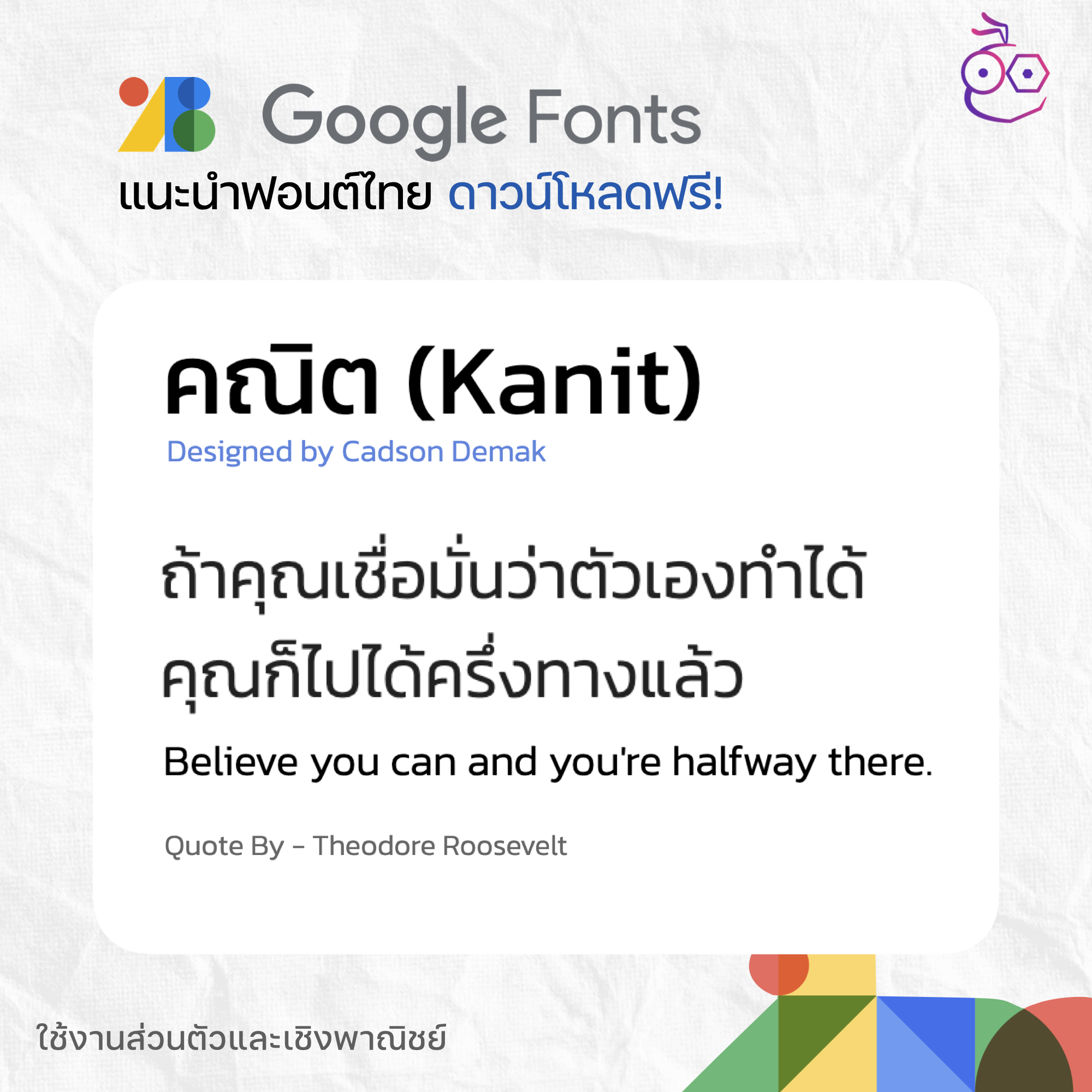
2. IBM Plex Sans Thai
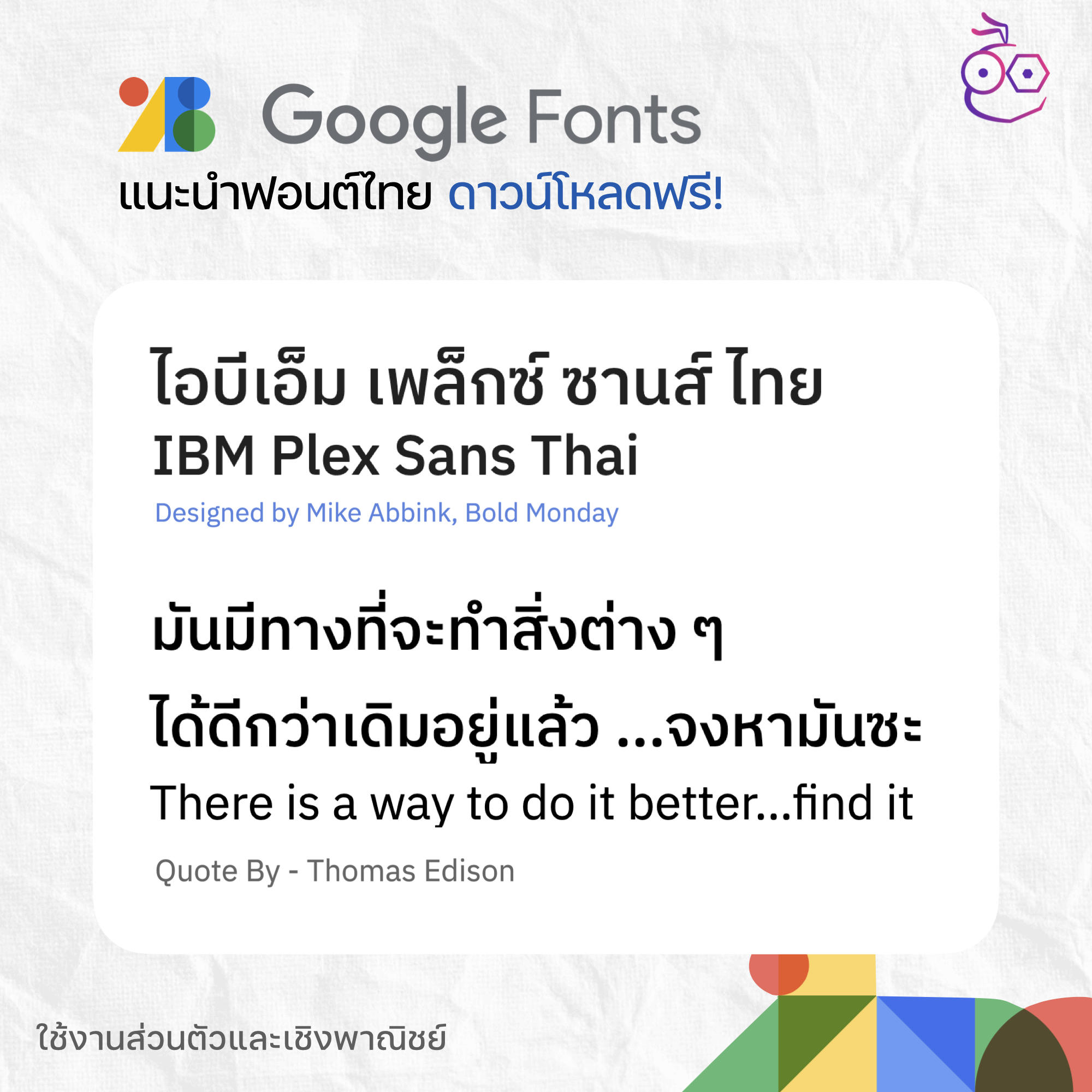
3. Noto Sans Thai
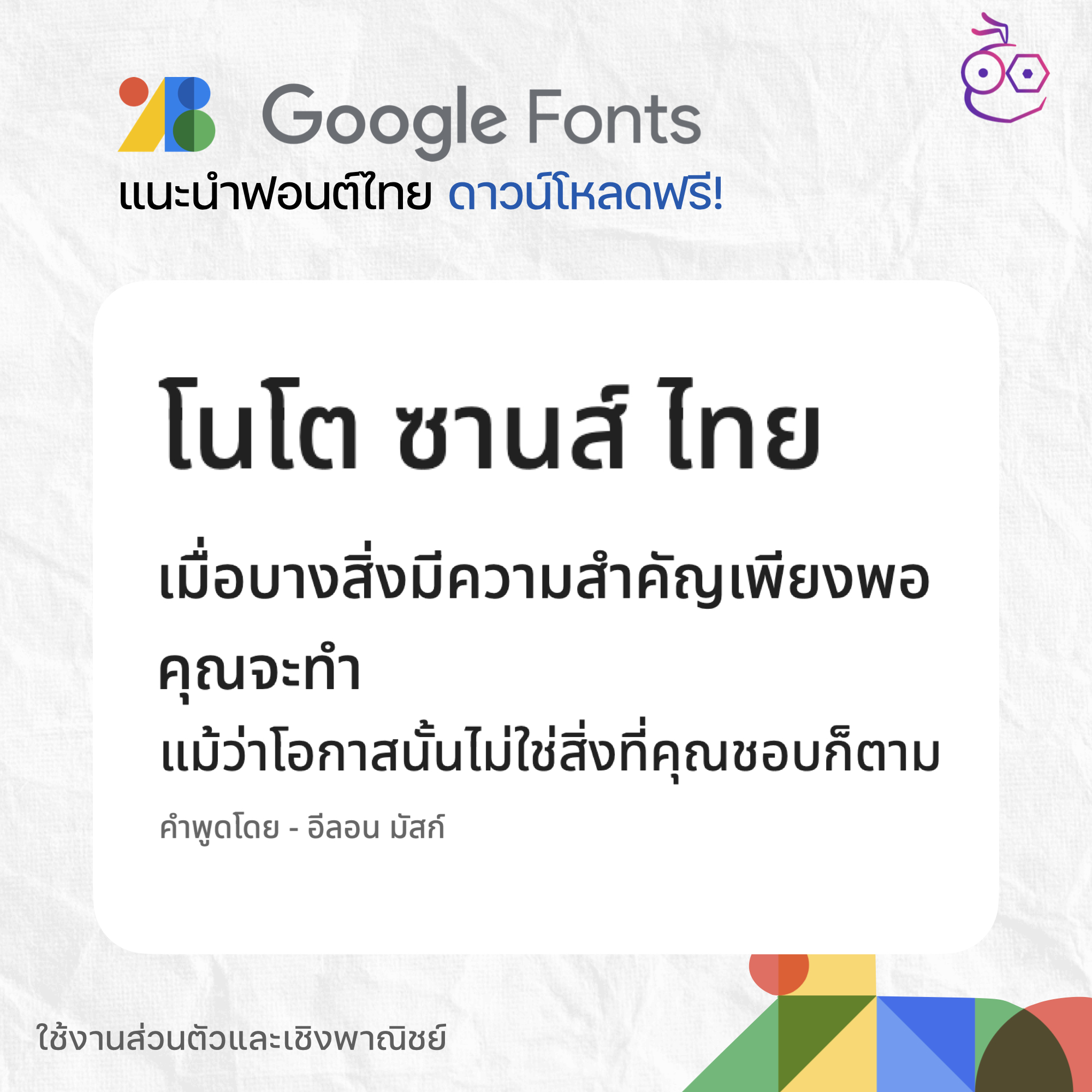
4. Mali
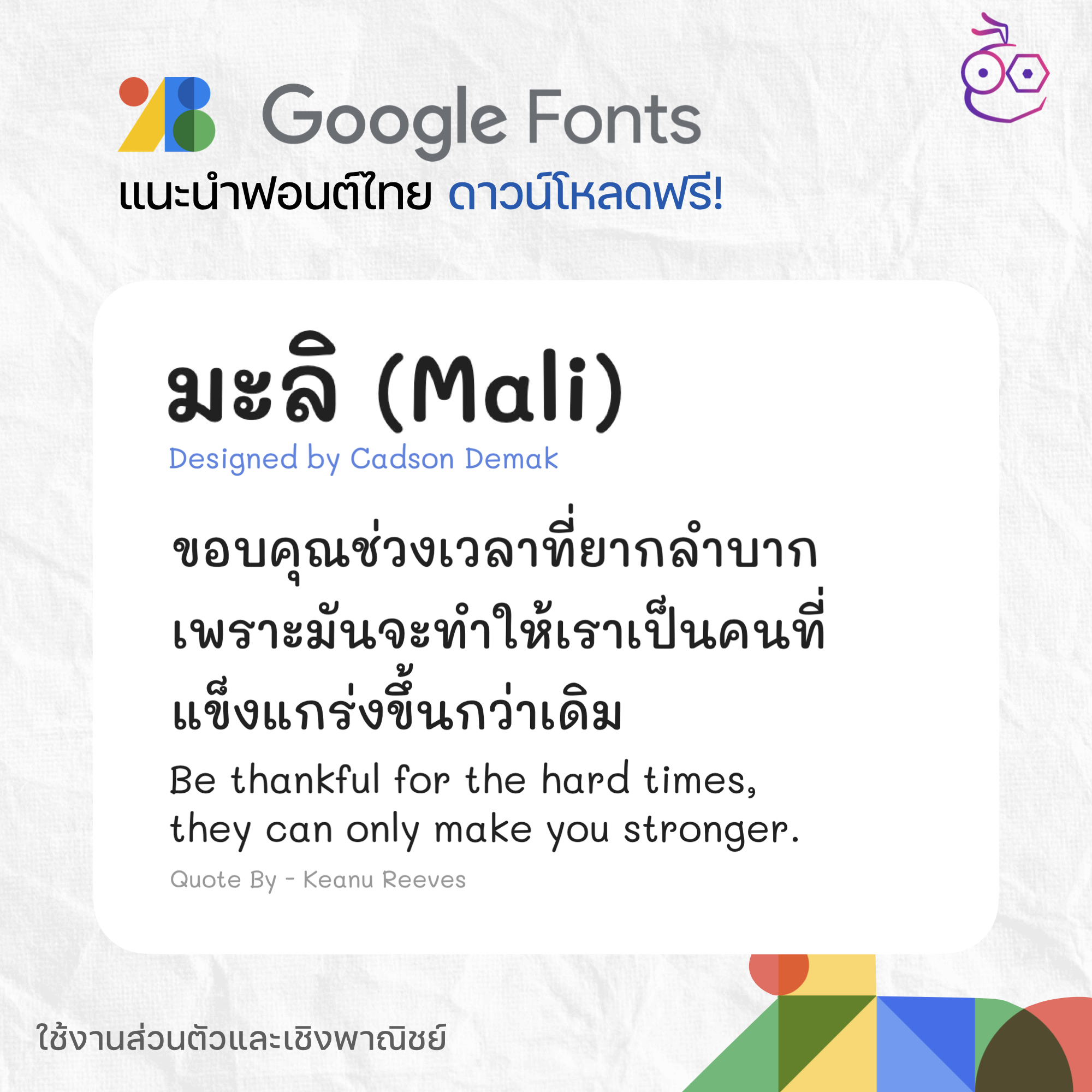
5. Chonburi
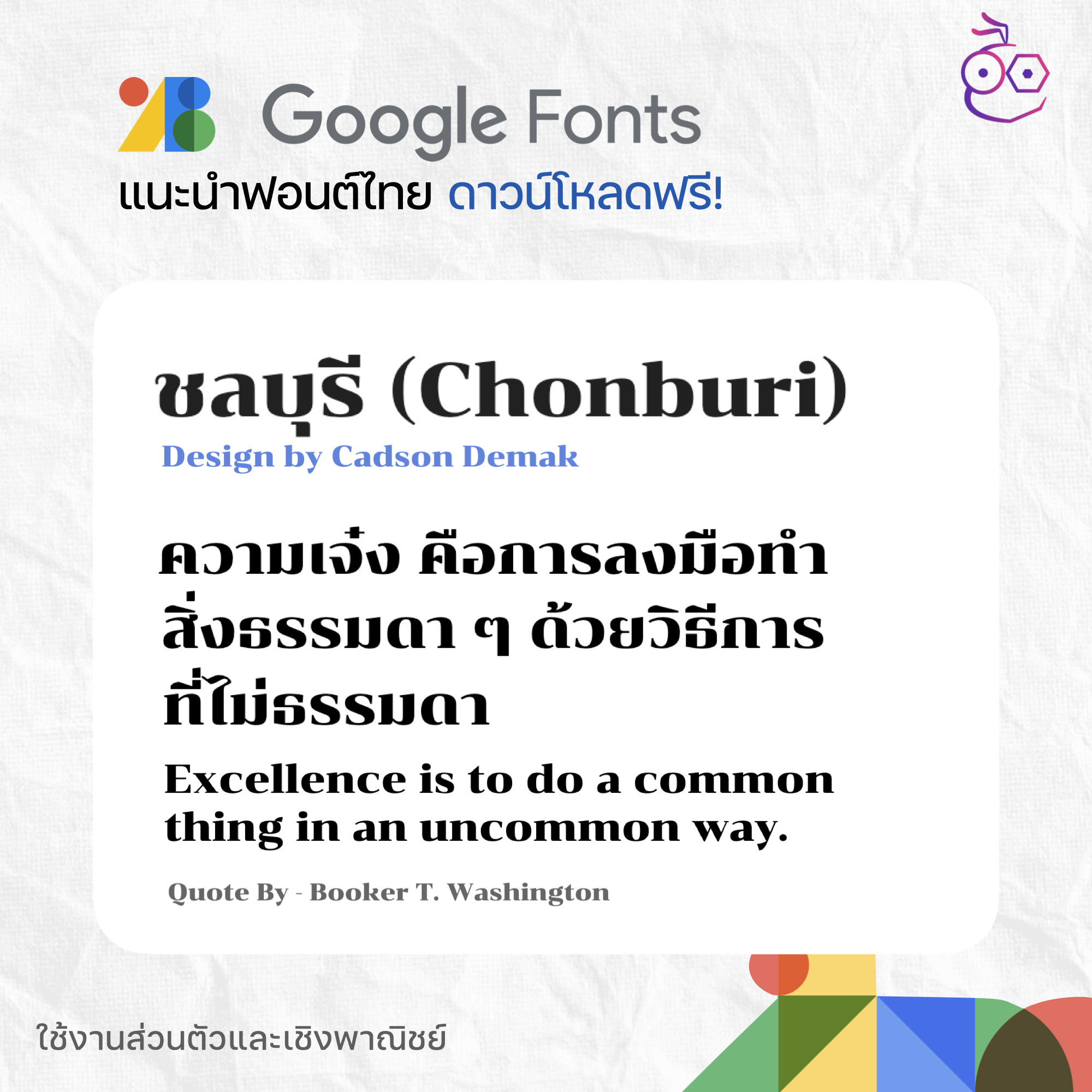
6. Pattaya
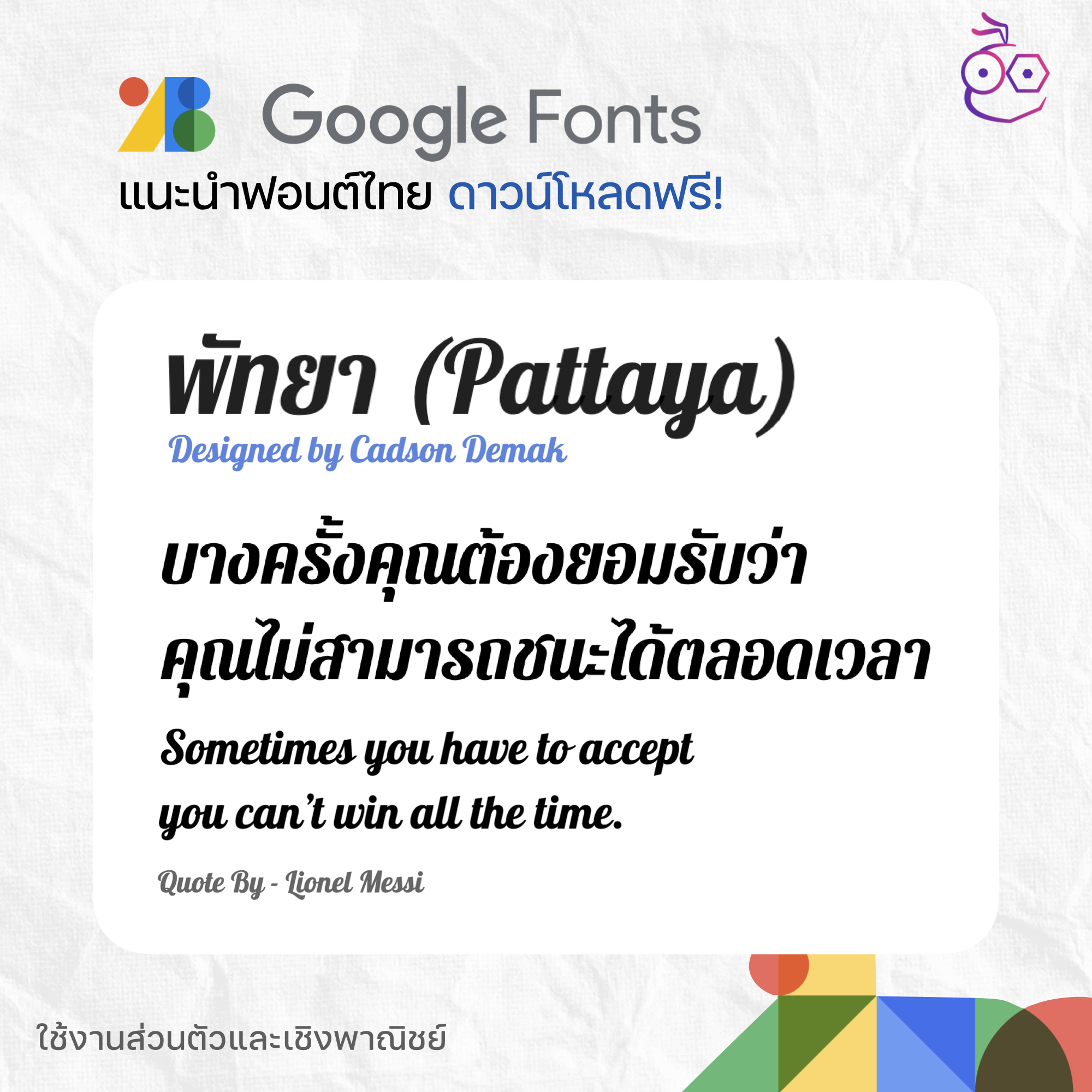
7. Mitr
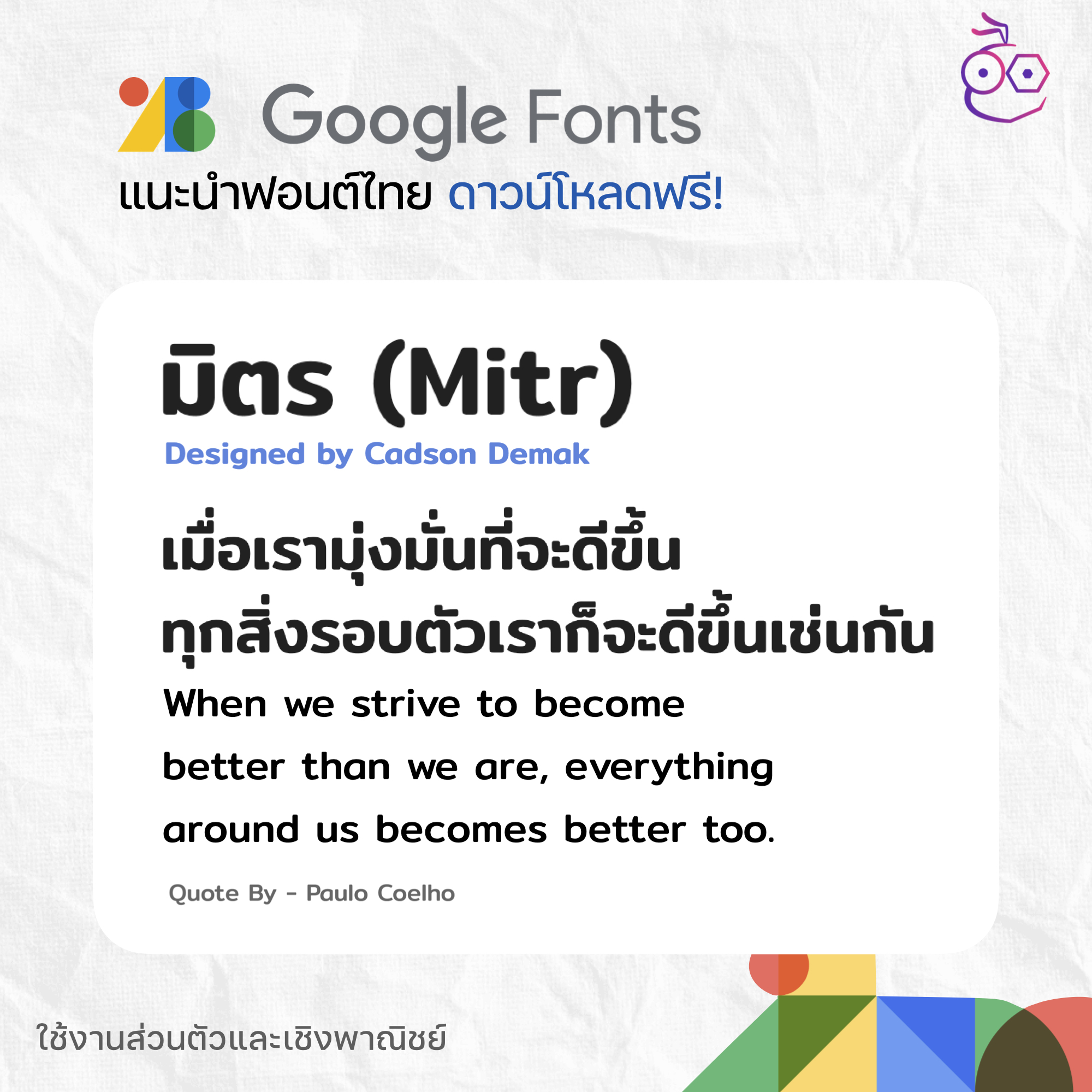
8. Prompt
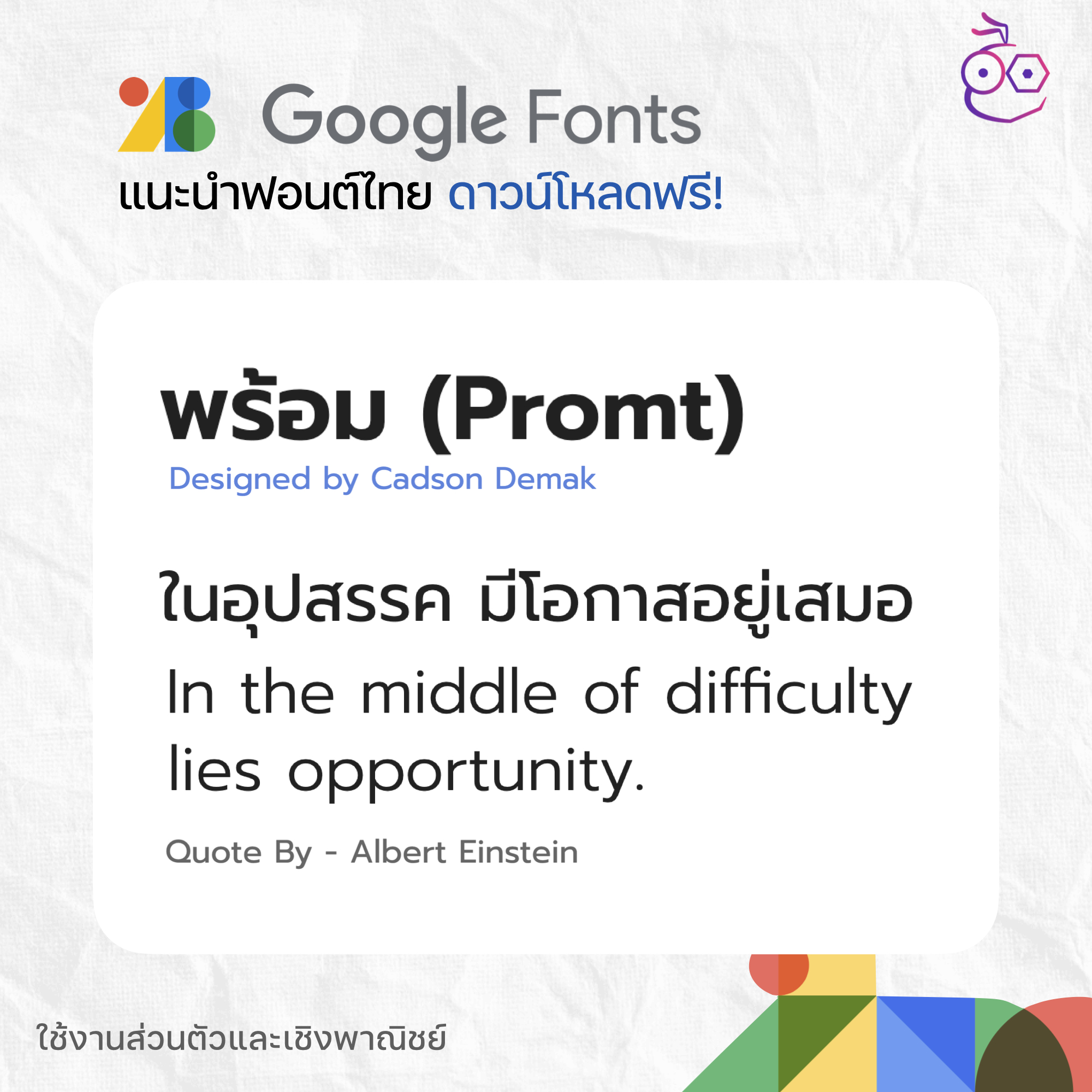
9. Athiti
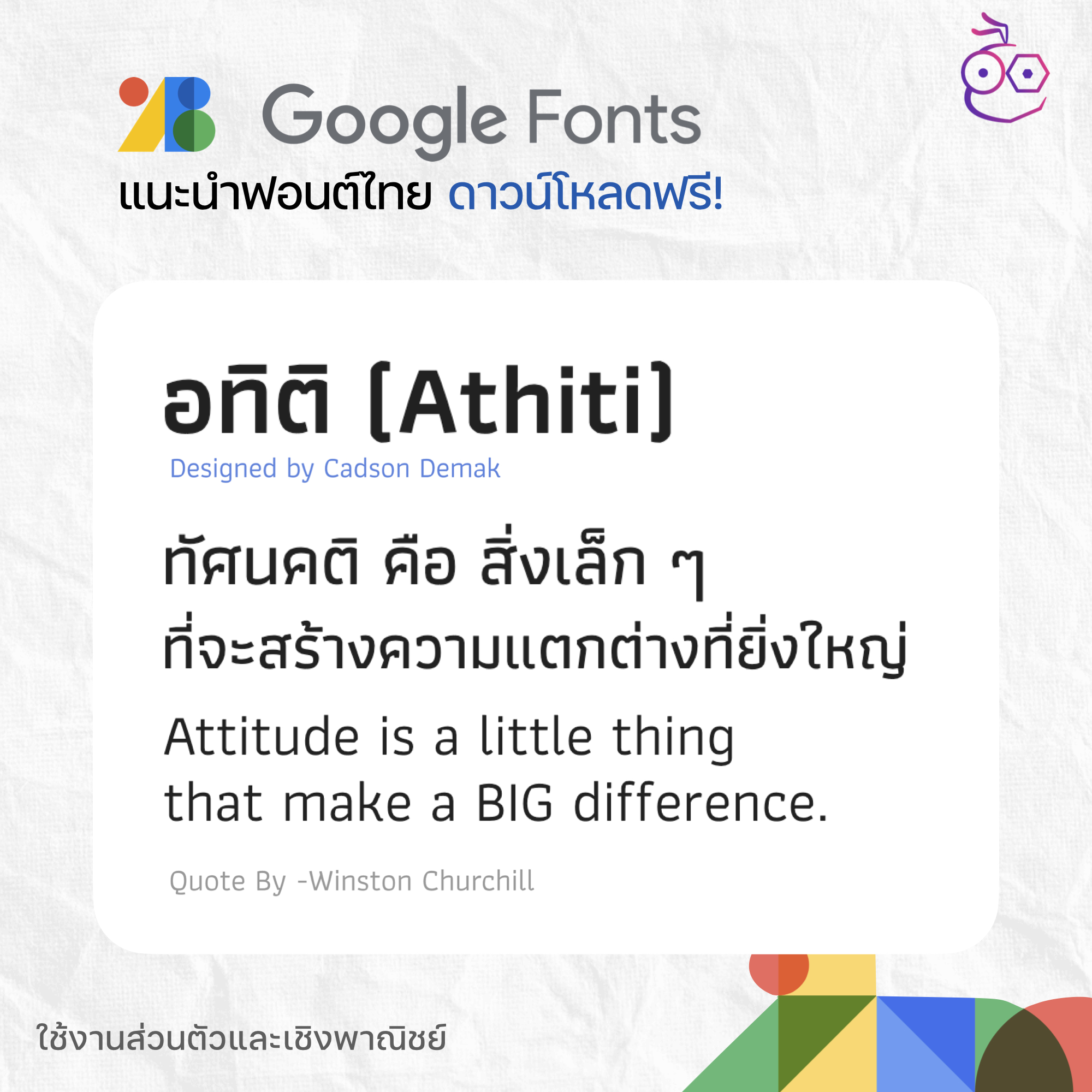
10. Sriracha